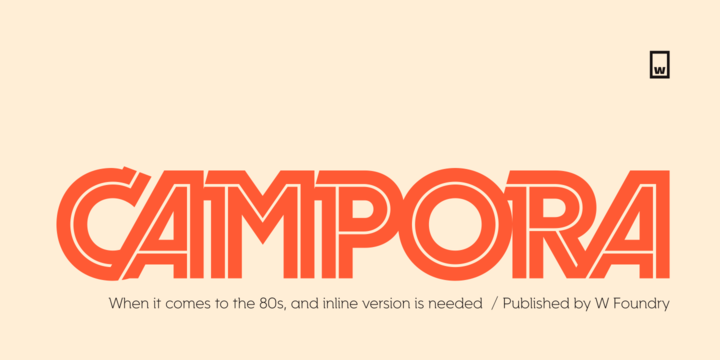
[Myfonts] Campora Font
В этом году мы посетили Болонскую детскую книжную ярмарку в Италии. В выходные дни мы отправились на Площадь Маджоре, чтобы посмотреть, что может предложить город, и, к счастью для нас, увидели невероятную вывеску магазина с надписью "CAMPORA". Мы сфотографировали напечатанный шрифт, а позже, вернувшись в студию, обнаружили, что это "Динамо". Сразу же наши умы были потрясены его красотой, и поэтому мы решили разработать новый шрифт, вдохновленный его острым и геометрическим дизайном, добавив новые веса и возможности OpenType. В процессе мы поняли, что и "Динамо", и один из наших любимых шрифтов Avant Garde, имеют схожую структуру, поэтому мы сделали типовой неоднородный шрифт между этими красотами, включая резкость "Динамо" и революционные лигатуры "Avant Garde".